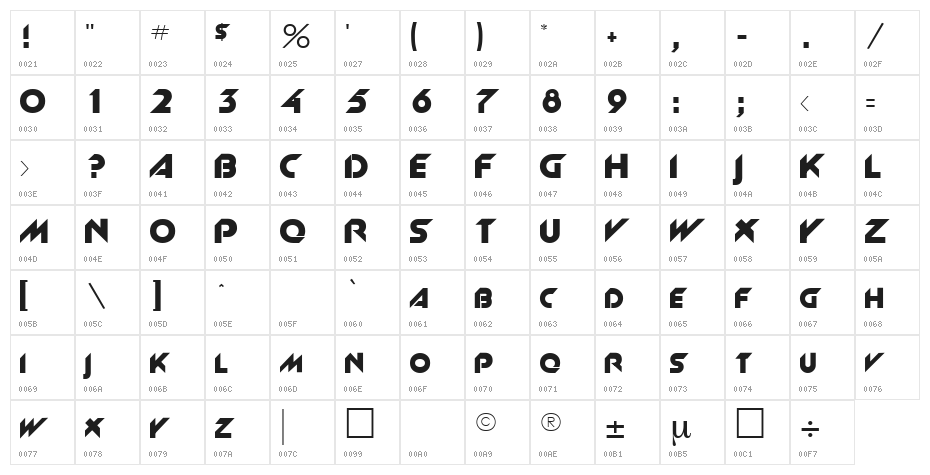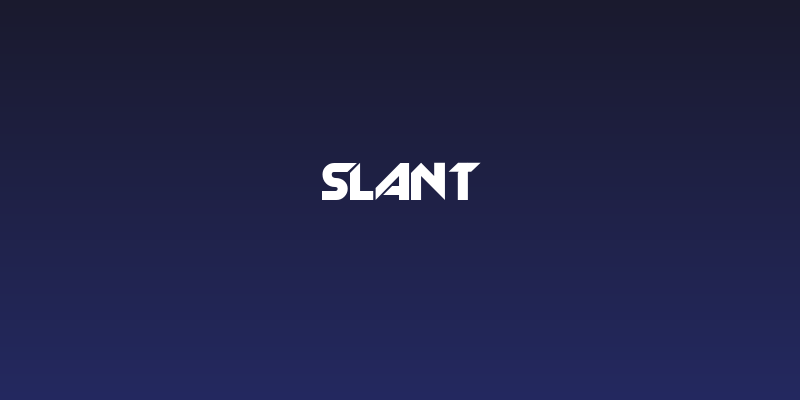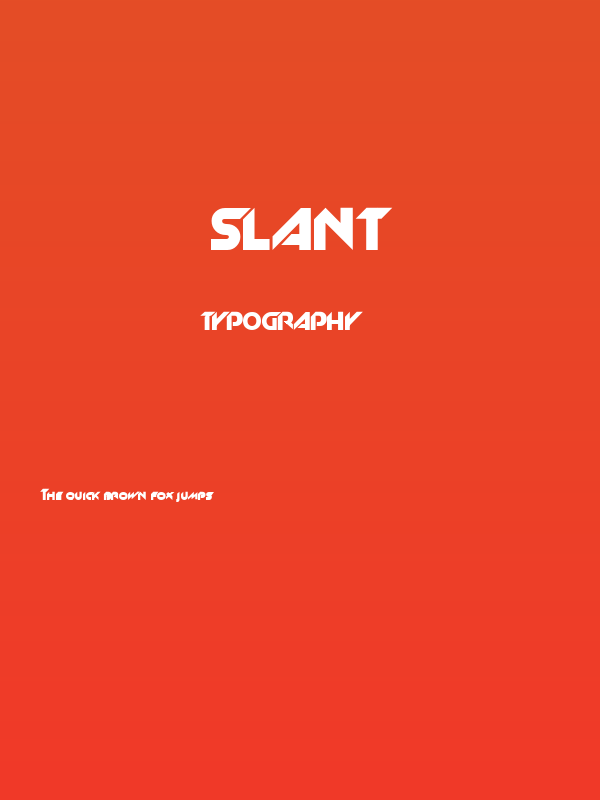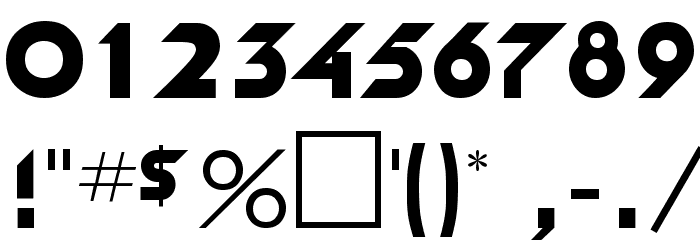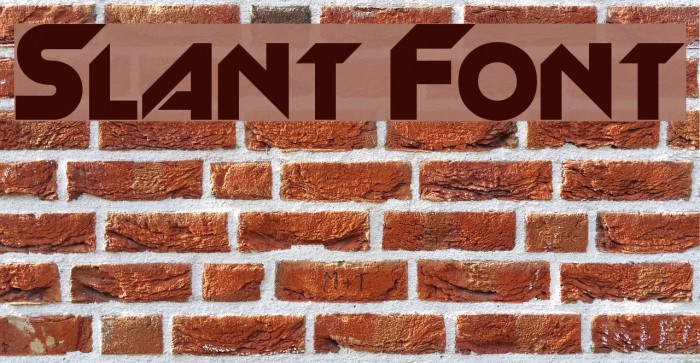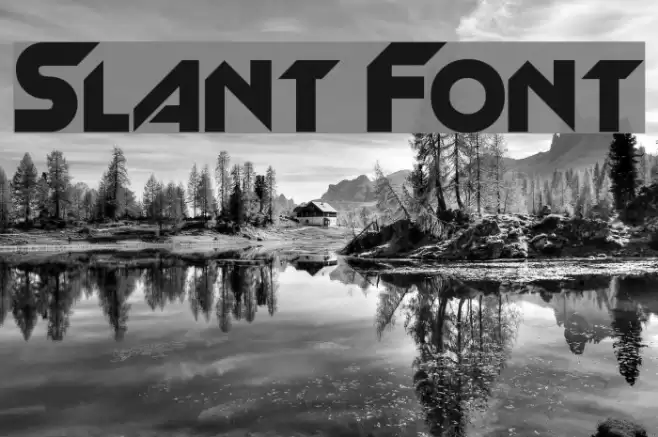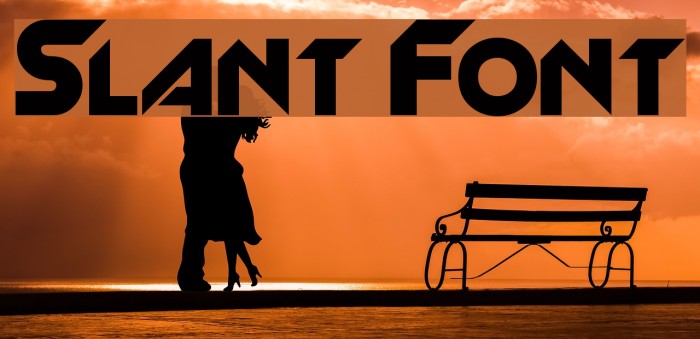
Slant Font
Fonts by Altsys Metamorphosis
| Estilo general | Futuristic |
| Proyectos propuestos | Ideal for sci-fi themed projects, modern branding, video game titles, and dynamic posters. |